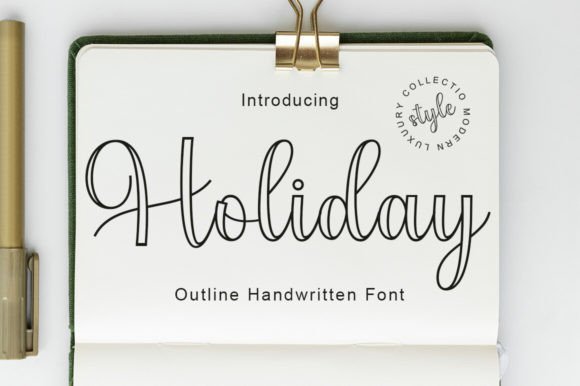
Holiday
Holiday : la police qui transforme chaque projet en œuvre d’art
Si vous cherchez une typographie à la fois charmante et élégante, ne cherchez plus : la police Holiday est le choix idéal. Inspirée de la calligraphie classique, cette police script allie finesse historique et modernité stylée, ce qui la rend parfaite pour sublimer n’importe quel support de communication.
- Design raffiné : chaque glyphe reflète un équilibre subtil entre courbes fluides et détails soignés, rappelant les manuscrits d’antan.
- Polyvalence exceptionnelle : idéale pour le branding, les titres, les designs de mariage, les invitations, les panneaux, les logos, les étiquettes et bien plus encore.
- Impact visuel élevé : grâce à son style distinctif, Holiday capte immédiatement l’attention et donne une impression de qualité premium.
En résumé, Holiday n’est pas seulement une police — c’est une véritable déclaration de style. Que vous créiez une invitation de mariage élégante ou un logo d’entreprise sophistiqué, cette police élèvera votre projet au plus haut niveau de professionnalisme.